Наши эксперты вспоминают самые популярные шрифты десятилетия.
Продолжаем исследовать лучшие шрифты разных десятилетий. В прошлых частях мы рассмотрели 1920-е и 1930-е годы, а сегодня обратимся к одному из самых драматичных периодов в мировой истории — 1940-м годам. В статье собраны не только шрифты, которые были созданы в это время, но и шрифты, появившиеся раньше, но громко заявившие о себе именно в 1940-е.
1940-е годы — десятилетие, ознаменованное глобальным конфликтом, послевоенным восстановлением и подъемом модернистских идеалов. Типографика той эпохи четко отражает эти драматические контрасты, а лучшие шрифты 1940-х сформировались одновременно под влиянием традиций и прогрессивных идей.
Но изучение типографических трендов того времени — не просто академическое упражнение, а ценный источник вдохновения для современных дизайнеров. Независимо от того, занимаетесь ли вы разработкой брендинга, версткой печатных изданий или экспериментальным искусством, эти культовые шрифты представляют собой настоящий мастер-класс по принципам дизайна и адаптивности и остаются актуальными по сей день.
Мы поговорили с ведущими экспертами в области типографики, чтобы составить список самых знаковых шрифтов 1940-х годов и узнать, как они повлияли и продолжают влиять на мировую визуальную культуру.
01. Ne-Po
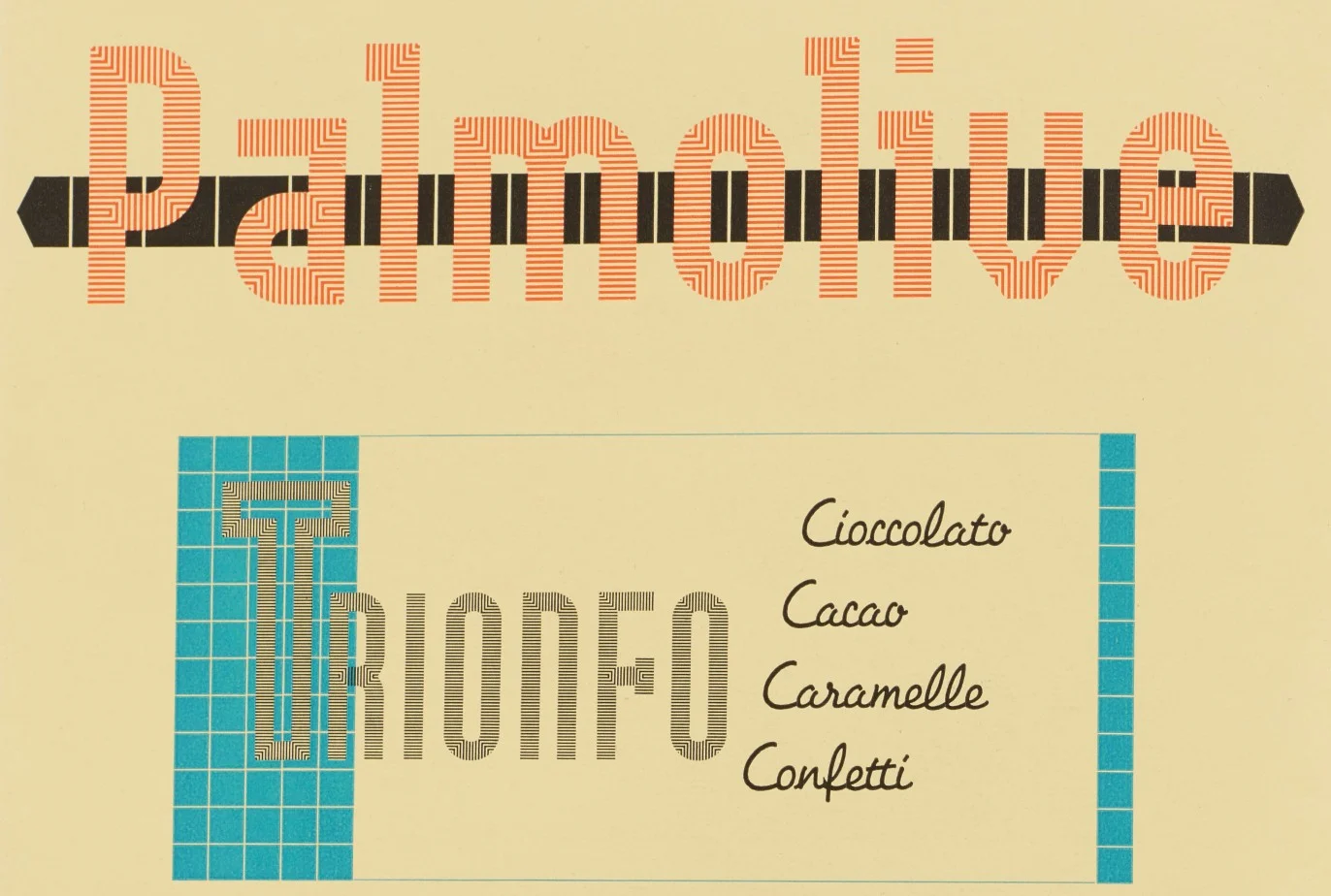
Шрифт Ne-Po (аббревиатура для «негативно–позитивный») представлял собой двойную систему блоков (модулей), которые можно было комбинировать для формирования букв, узоров и декоративных обводок. Серия NE включала буквы, состоящие из негативного пространства, а серия PO — «позитивные» формы из линий. Адаптивность этого модульного шрифта сделала его популярной опцией для создания экспериментальной типографики в 1940-х годах.
Саймон Манчипп, соучредитель SomeOne, описывает его так: «Модульное чудо, игра негативного и позитивного пространства. Созданный в начале 1930-х годов немецкой типографией Brüder Butter, позже переименованной в Schriftguss, этот шрифт был не просто набором букв, а целой системой. Концепцией. Источником бесконечного творчества. Серия Negative — 17 тщательно проработанных модулей с незапечатанными буквами и 15 модулей серии Positive. Вместе они были не просто шрифтом, а инструментами. Для создания обводок, узоров и расширения границ визуальной коммуникации».
Хотя изначально он был создан для латинского алфавита, его модульная система вдохновила на адаптацию шрифтовых дизайнеров из других стран, в частности Индии. «Там он преобразился, — отмечает Саймон. — Теперь это не только латинские буквы, но и гуджарати и маратхи — смелый, изобретательный шаг, соединяющий культуры. Шрифт стал рассказчиком. Декоративный шрифт превратился в произведение искусства».
02. Futura
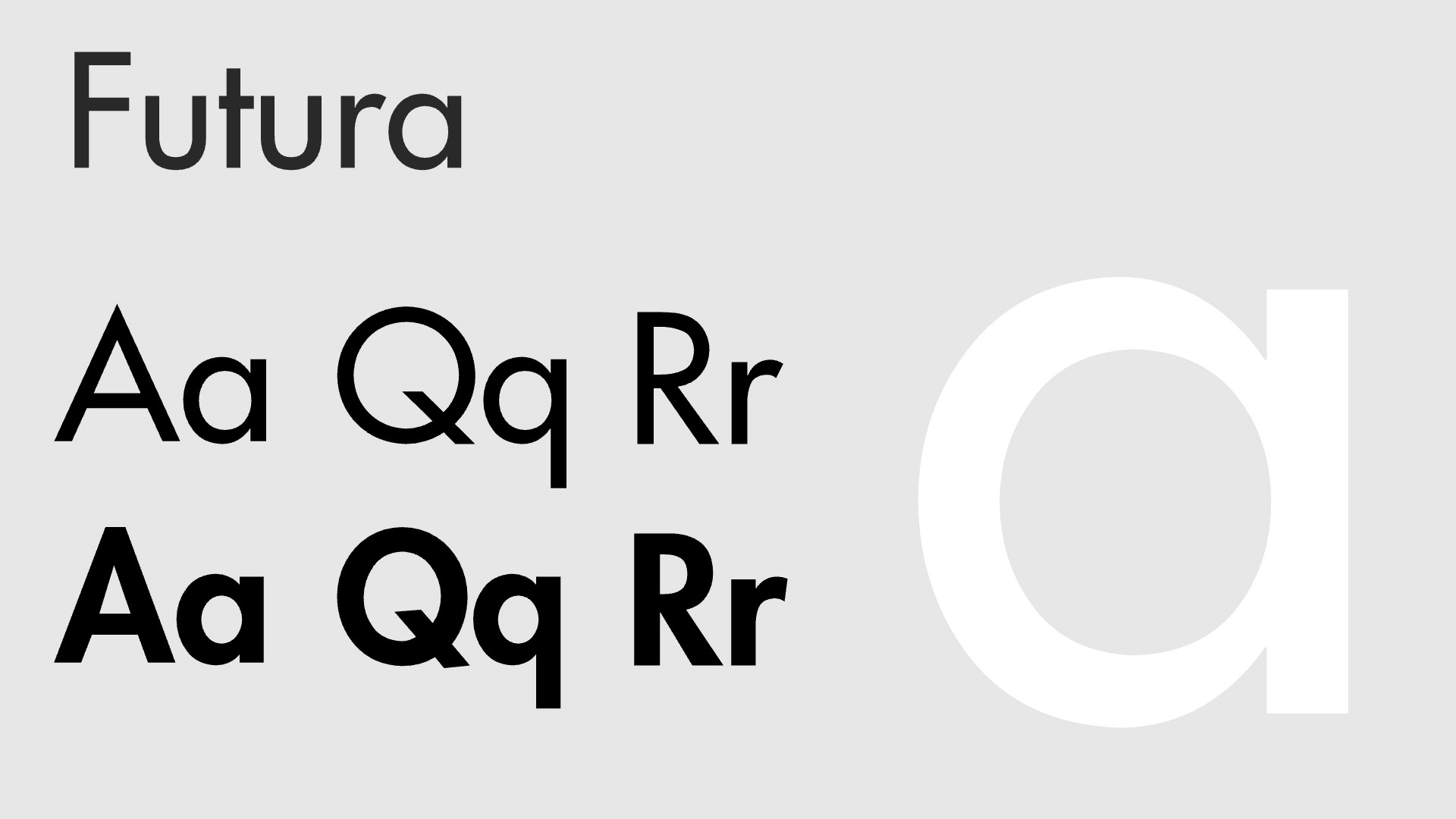
Futura — геометрический гротеск, созданный Полом Реннером и впервые выпущенный в 1927 году. К 1940-м годам он прочно утвердился в качестве визитной карточки модернистской типографики благодаря сочетанию чистых линий, геометрической точности эстетики Баухауса и высокой практичности.
Futura отвергает влияние истории и декоративные детали в пользу простых геометрических форм — кругов, треугольников и прямоугольников. Высокие верхние выносные элементы, низкоконтрастные штрихи и почти идеально круглые буквы «o» и «a» сделали его эффективным как для основного текста, так и для заголовков.
«Для 1940-х годов Futura выглядит особенной», — с энтузиазмом говорит Гарри Сандху, старший креативный директор Jung von Matt London. «Ее чистая геометрия была не просто модернистской, она была заявлением. В мире, жаждущем порядка среди хаоса, этот шрифт стал символом прогресса. От пропагандистских плакатов до печатных изданий, он не просто занимал место на странице, он говорил с аудиторией».
03. Garamond
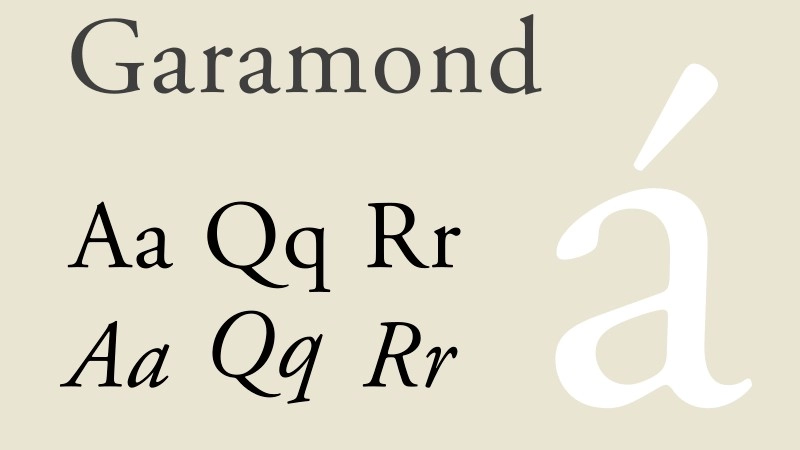
Названный в честь французского гравера XVI века Клода Гарамона, Garamond — это неподвластный времени шрифт с засечками, который вновь обрел популярность в 1940-х годах. В тот период его особенно часто можно было встретить в книгах и полиграфии. Его изящные, гуманистические формы и сбалансированные пропорции делают его одним из самых читаемых и элегантных шрифтов в истории.
В мире, переживающем стремительные изменения, Garamond символизировал традиции и надежность. Его повсеместное использование в газетах, журналах и официальных документах подчеркивало его универсальность и неизменную привлекательность. «Garamond выступал противовесом прогрессивной Futura», — отмечает Гарри Сандху. «В частности, его версии, выпущенные ATF и Monotype».
«Там, где Futura толкала нас вперед, Garamond помогал нам сохранить связь с действительностью. Его гуманистические штрихи придавали книгам, журналам и рекламным объявлениям теплоту, тихую уверенность, говорящую о традициях и постоянстве. Вместе они отражали напряжение 1940-х годов: потребность в стабильности и вместе с тем стремление к чему-то новому».
04. Palatino
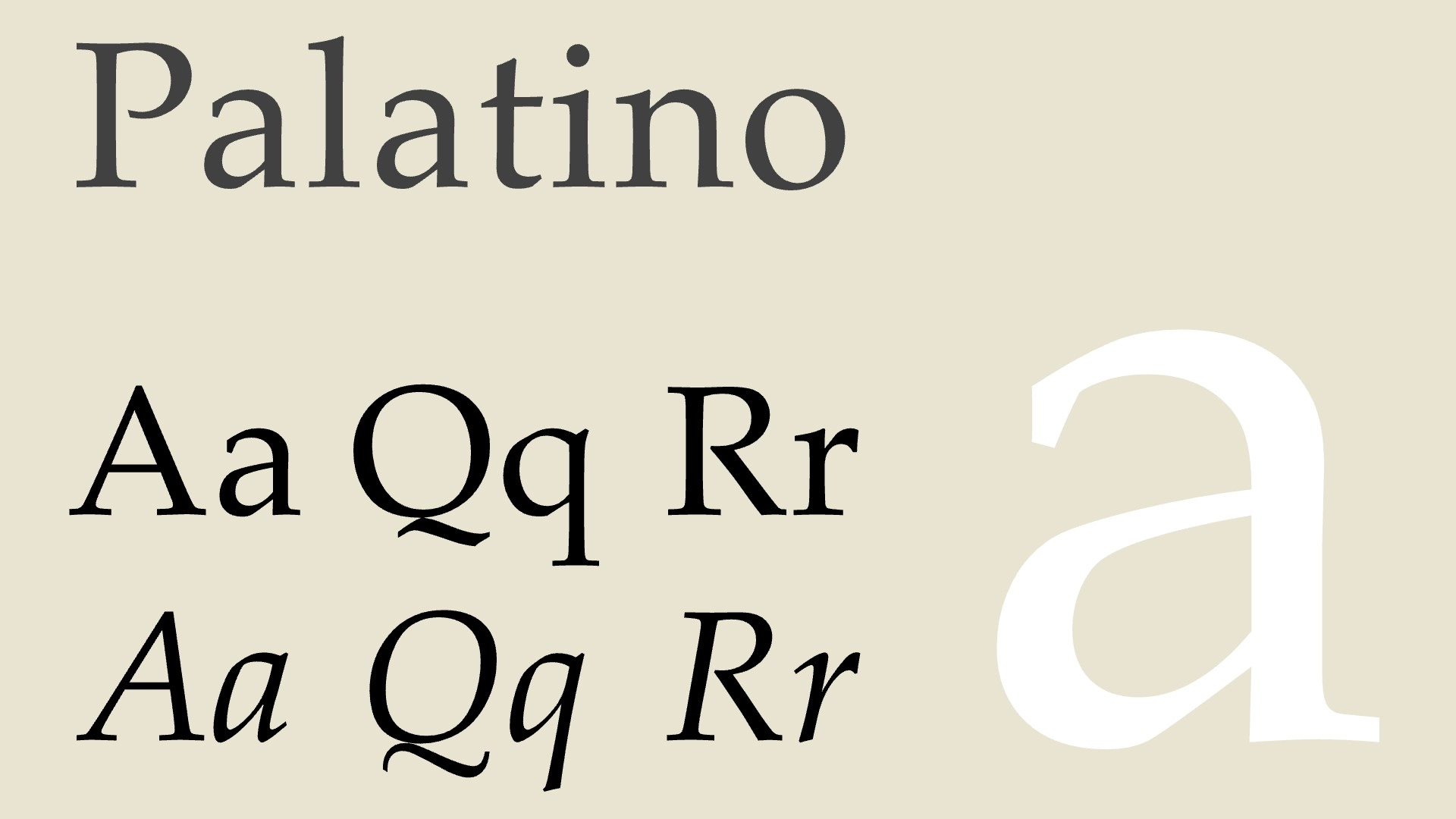
Palatino — классический шрифт с засечками, разработанный Германом Цапфом и выпущенный в 1948 году. Вдохновленный антиквами итальянского Возрождения, он известен своей высокой читаемостью и универсальностью, и поэтому широко используется как для основного текста, так и для заголовков. Умеренный контраст штрихов и изящные засечки придают ему классический, традиционный вид.
Брендан Мерфи, креативный директор Lippincott, испытывает особую симпатию к этому шрифту. «После окончания средней школы в Дублине, одной из моих первых работ стала работа в небольшой дизайнерской студии, которая специализировалась на годовых отчетах», — вспоминает он. «Мы делили офис с типографией, работавшей на фотонаборной машине Linotype. Они научили меня простым операциям со шрифтом Palatino. Я никогда не спрашивал, почему именно этот шрифт: возможно, он был немного более человечным и менее формальным, чем Times. И, скорее всего, одним из немногих шрифтов, которые у них были».
В любом случае, для Брендана это была любовь с первого взгляда. «Palatino был открытым и каллиграфическим, с высокими строчными буквами», — объясняет он. «Курсивное начертание, применяемое для цитат и подписей, имело совершенно другую текстуру, больше напоминавшую изящное письмо. Этот шрифт обладает уверенным универсальным голосом, который подходит для самых разных отраслей, от сельского хозяйства до нефтяной промышленности».
Тем не менее, он признается, что не использовал Palatino более 40 лет. «Когда я приехал в Америку учиться в школе дизайна, мои учителя предпочитали Garamond и Frutiger. Возможно, пришло время по-новому взглянуть на него и попробовать еще раз?»
05. Franklin Gothic Condensed
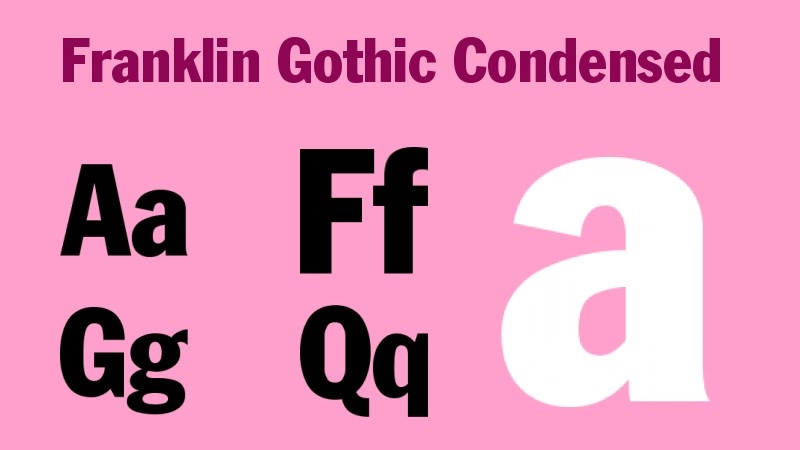
Franklin Gothic Condensed — гротеск, который отличается сильными геометрическими формами, чистыми линиями и сжатыми буквами. Выразительный и смелый, он воплощает в себе дух ар-деко и часто используется для заголовков, плакатов и вывесок.
«Разработанный Моррисом Фуллером Бентоном в 1948 году, Franklin Gothic Condensed — это шрифт, который является синонимом слова “бизнес”», — говорит Уэйн Дикин, директор Wolff Olins. «Благодаря своим энергичным, плотным буквам он стал незаменимым инструментом эффективной коммуникации. Считайте его рабочей лошадкой послевоенного дизайна — он использовался везде, от газет до промышленных плакатов. Даже General Electric предпочла именно этот шрифт, чтобы продемонстрировать аудитории уверенность в период инноваций и роста».
И он остается популярным до сих пор. «Не так давно газета The Guardian сделала Franklin Gothic частью своей печатной и цифровой айдентики, чтобы модернизировать типографский язык и при этом сохранить сильный голос бренда», — отмечает Уэйн. «Универсальный Franklin остается идеальным выбором для компаний, стремящихся поддерживать баланс между традициями и современной привлекательностью».
06. Brush Script
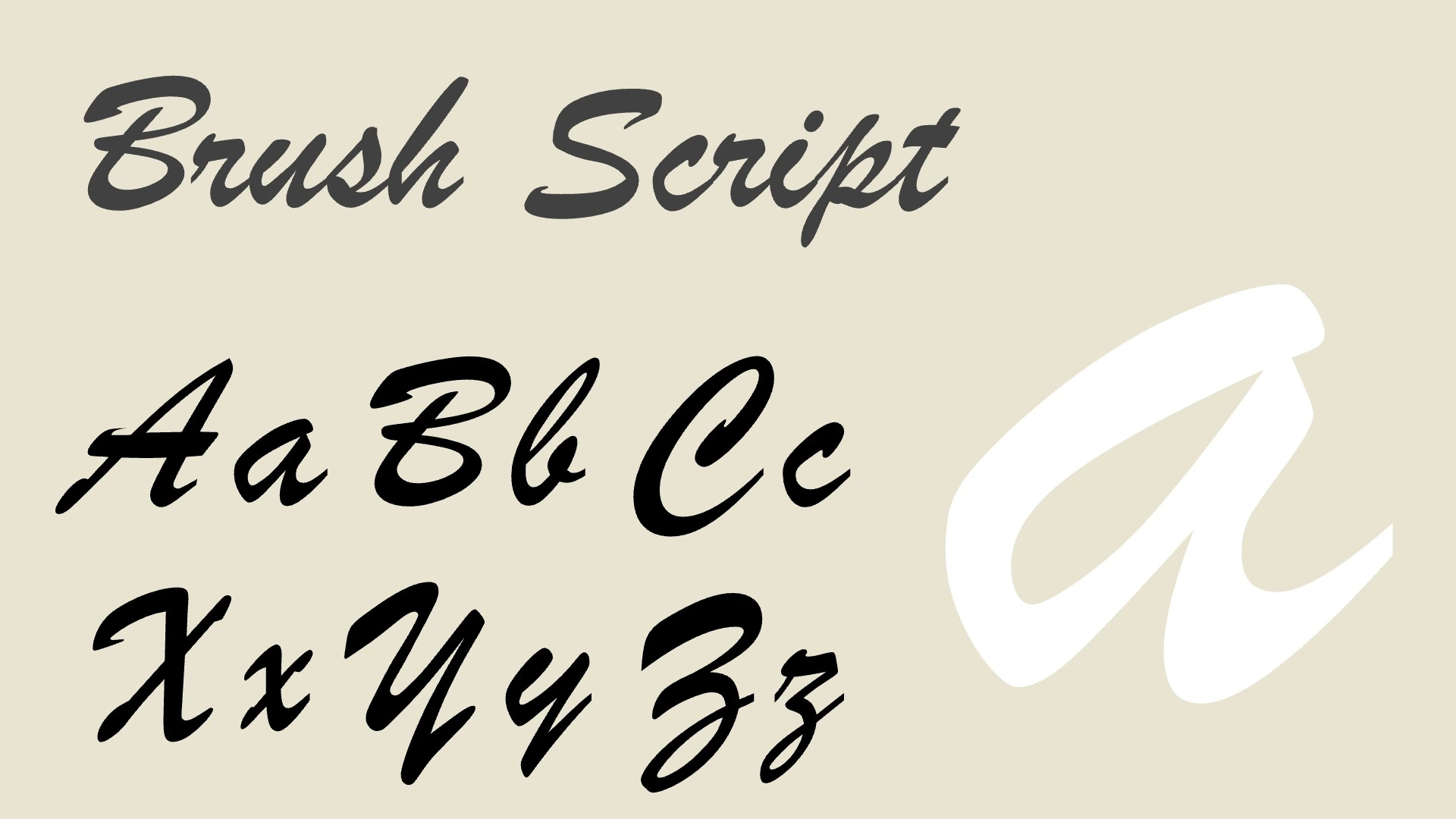
Brush Script — рукописный шрифт, имитирующий каллиграфию. Его плавные, выразительные формы и связанные буквы создают ощущение неформальности и элегантности. По этой причине Brush Script часто используют для приглашений, логотипов и других сценариев, где требуется подобная эстетика.
«Созданный Робертом Э. Смитом в 1942 году, Brush Script стал глотком свежего воздуха в достаточно традиционное время», — объясняет Уэйн Дикин. «Его плавный, рукописный стиль обладал теми индивидуальностью и теплотой, которыми бренды никак не могли насытиться».
Он приводит несколько примеров. «Курорт Butlin's выбрал Brush Script в качестве центрального элемента своей визуальной идентичности в середине XX века. Его жизнерадостная доступная эстетика идеально сочеталась с обещанием веселого семейного отдыха. Совсем недавно Kärcher, немецкий бренд оборудования для уборки и очистки, использовал Brush Script в маркировке продуктов ретро-линейки, что подтверждает непреходящее очарование этого шрифта для разных отраслей».
07. Trade Gothic
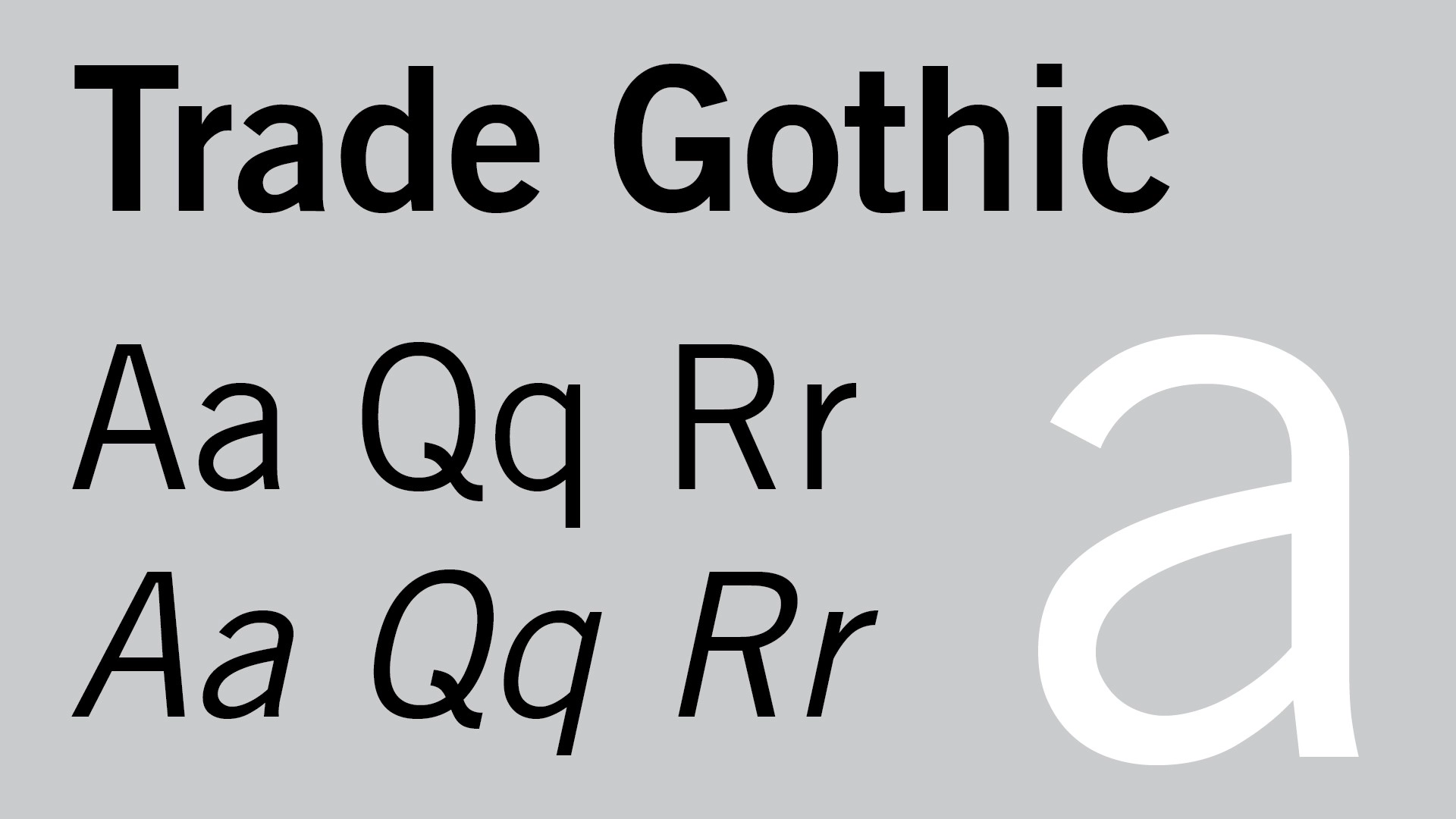
Trade Gothic — шрифт без засечек, разработанный в 1948 году Джексоном Берком. Как и многие готические шрифты XIX и начала XX веков, он имеет более неправильные формы, чем другие гротески, появившиеся позднее, например, Helvetica и Univers, что делает его отличной опцией для тех, кто ищет что-то более характерное.
«Этот шрифт воплощает в себе трудолюбивый дух своей эпохи», — говорит Райан Спенс, старший креативный директор Born Ugly. «Его высокие строчные буквы и гуманистические черты отражают ясность и мастерство, игравшие важную роль в газетной печати 1940-х годов».
Trade Gothic обладает теми качествами, которые мы ценим в дизайне середины века: эффективность, целеустремленность и надежность. «Глядя на блочные заглавные буквы, мы будто слышим гул и стук печатных машин. В эпоху, когда люди стремятся к тактильности и ностальгии, такая теплая аутентичная типографика обеспечивает практически осязаемую связь с тем временем, когда приоритетом в дизайне были функциональность и человечность».
08. Highway Gothic
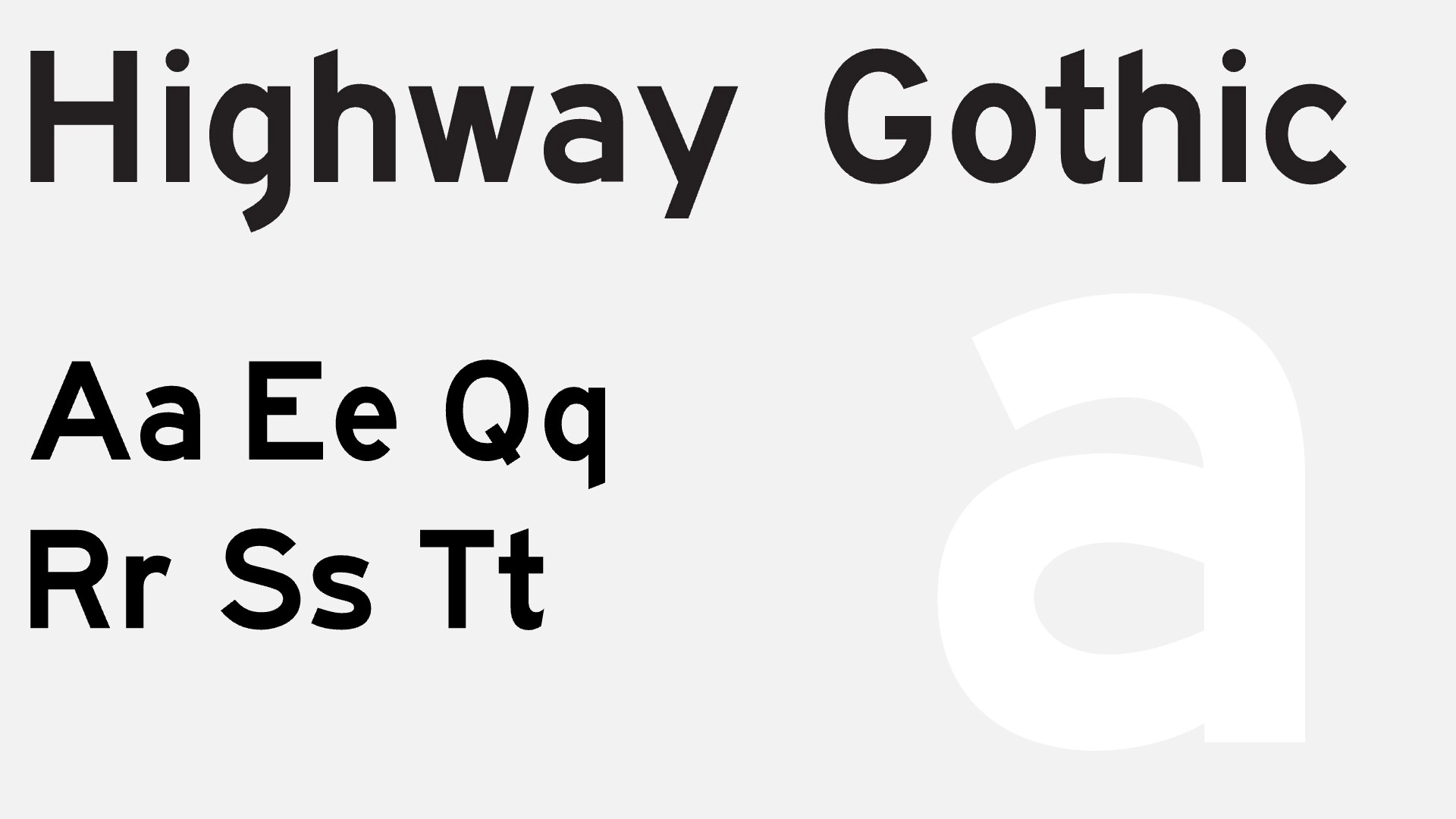
Highway Gothic — гротеск, разработанный Федеральным управлением автомагистралей США (FHWA). «Впервые опубликованная в 1948 году в стандартных алфавитах FHWA и позже обновленная в 2000 году, эта серия шрифтов используется для дорожных знаков в США и многих других странах», — говорит Роуз Стюарт, директор по дизайну в The Frameworks.
«Как ценитель типографики дорожных знаков я очень люблю этот шрифт», — добавляет она. «Такое использование требует высокого уровня разборчивости с большого расстояния и на высокой скорости. Серия состоит из шести шрифтов, адаптированных для различных сценариев, от вывесок на автомагистралях до наземных и световых знаков».
09. Lydian
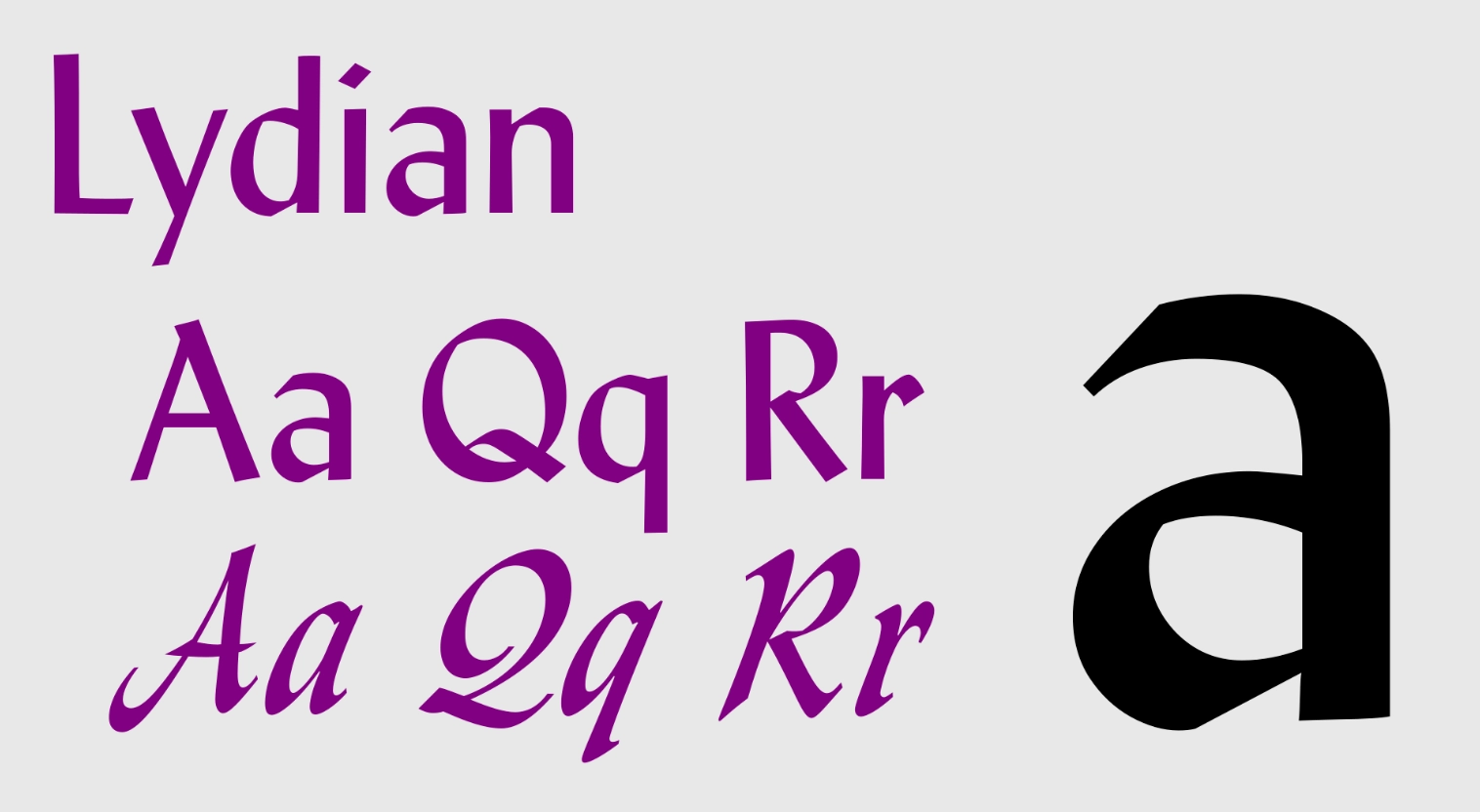
Lydian — каллиграфический гуманистический шрифт без засечек, разработанный Уорреном Чаппеллом для American Type Founders в 1938 году. Он наиболее известен как шрифт из финальных титров телесериала «Друзья». Но, как отмечает Питер Гаскелл, дизайн-лид в Dalziel & Pow, впервые он громко заявил о себе в 1940-х годах.
«Lydian всегда был для меня источником вдохновения, особенно в детстве, когда я поглощал научную и популярную литературу 40-х и 50-х годов», — вспоминает он. «Он казался полным таинственности и характера, но при этом никогда не был слишком вычурным. Он был повсюду: на обложках книг, в брендинге отелей, галереях и государственных учреждениях, даже в титрах популярных телешоу».
«Его трудно отнести к какому-то конкретному времени и характеру», — добавляет Питер. — «Это что-то колдовское? Академическое? Причудливое? Lydian невероятно трудно классифицировать. И как дизайнер, я считаю, что эта гибкость — часть того, что делает его неподвластным времени».